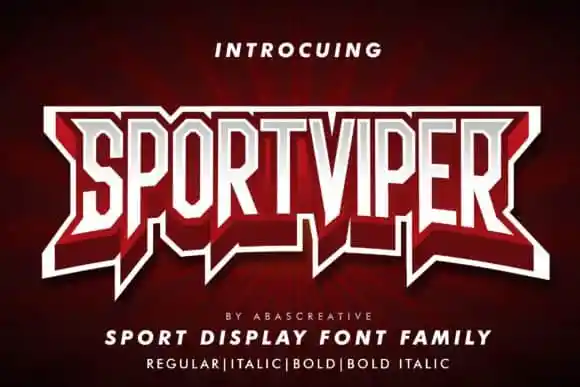
A Sport Viper Display Font é inspirada nos filmes de ficção científica, apresentando uma aparência moderna e limpa que combina perfeitamente com conceitos futuristas. Esta tipografia foi desenhada e compartilhada pela AbasCreative, conhecida por suas fontes bold e autênticas para ambientes visuais criativos. Ideal para uso em aplicações gráficas como posters, redes sociais, headlines, conteúdo online, interfaces de usuário, títulos e mesmo grandes formatos, a Sport Viper é um elemento poderoso capaz de destacar suas ideias inovadoras. Com seu design bold e autêntico, essa fonte é perfeita para tornar sua mensagem ainda mais impactante em qualquer espaço onde desejará usá-la.